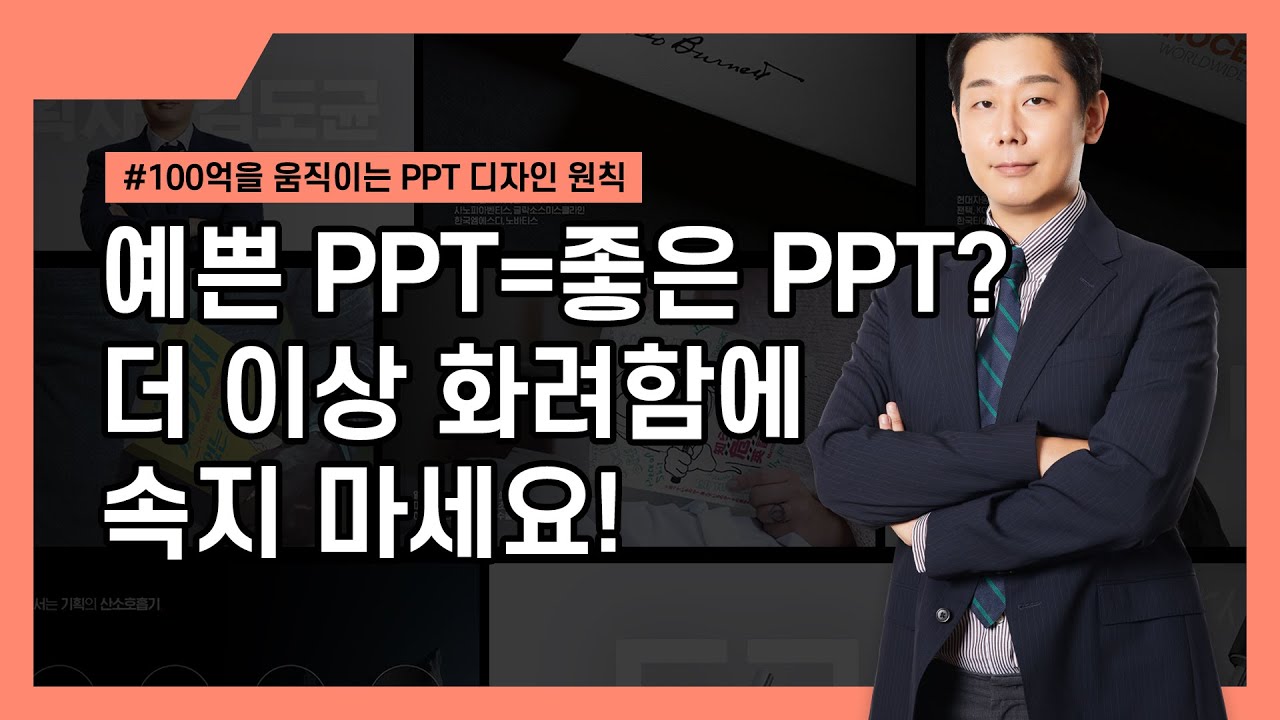
페이퍼로지 — 이주임 X 김도균에서 배포하는 무료 폰트입니다. PPT 도형에 넣으면 중앙에 딱 맞는 발표용 고딕
프레젠테이션 디자이너 이주임 님과 PPT 유튜버 김도균 님이 함께 만든 서체입니다. 이름은 김도균 님의 채널명에서 그대로 왔습니다.
이 서체에는 먼저 밝혀야 할 것이 있습니다. **완전히 새로 그린 폰트가 아니라 기존 폰트를 재조합해 개량한 파생 폰트**입니다. 한글은 G마켓산스, 영문은 몬세라트, 일본어는 M PLUS 2를 결합했고, 만든 목적은 G마켓산스를 파워포인트에서 쓰기 좋게 변형하는 것이었습니다. 원본이 모두 오픈 라이선스라 법적으로는 문제가 없습니다.
그래서 내세우는 특징이 조형이 아니라 실무 문제 해결입니다. 네 가지를 꼽습니다. **글자와 도형의 높이 중심을 맞췄고**, 윈도우에서도 텍스트 투명 윤곽선이 필요 없으며, 파워포인트에서 커닝이 잘 적용되고, **한눈에 수치를 비교할 수 있는 고정폭 숫자**를 넣었다는 것입니다. 도형 안에 글자를 넣었을 때 어긋나던 문제, 글자가 얇게 깨져 보이던 문제, 표에서 숫자 자리가 흔들리던 문제를 각각 겨냥한 것입니다.
굵기가 Thin부터 Black까지 아홉 가지로 이 목록에서 가장 넉넉합니다. 현대 한글 11,172자를 모두 담았습니다. 슬라이드와 문서에 맞고, 이름과 달리 명조가 아니라 고딕이니 참고하세요. 오픈 폰트 라이선스로 배포되어 수정과 재배포가 자유롭습니다.